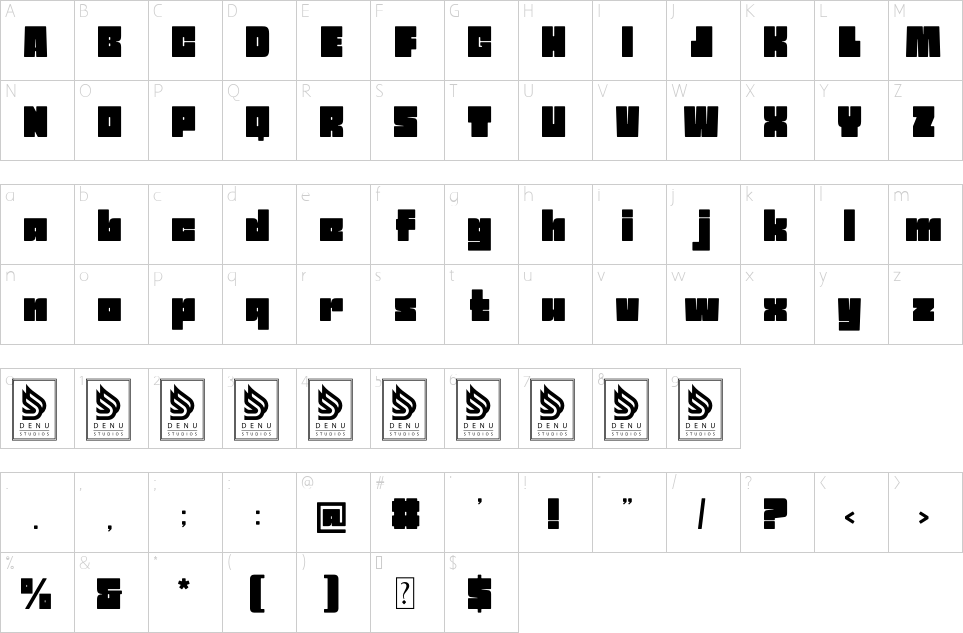
A fonte Mono Cubic é uma escolha perfeita para aqueles que procuram um estilo moderno e minimalista. Desenvolvida pelo Designer desconhecido Gracetypestudio, esta fonte vem em versões para Windows e Mac. Com seu design clean e simples, a Mono Cubic combina perfeitamente com qualquer projeto digital, seja para um site, um livro digital ou até mesmo para criar um design gráfico minimalista. Com um design minimalista e moderno, esta fonte garante um resultado proeminente e elegante, sem se atrasar com excessões desnecessárias. Com um design único e limpo, a Mono Cubic está disponível gratuitamente para quem procura novas fontes para suas criações digitais.